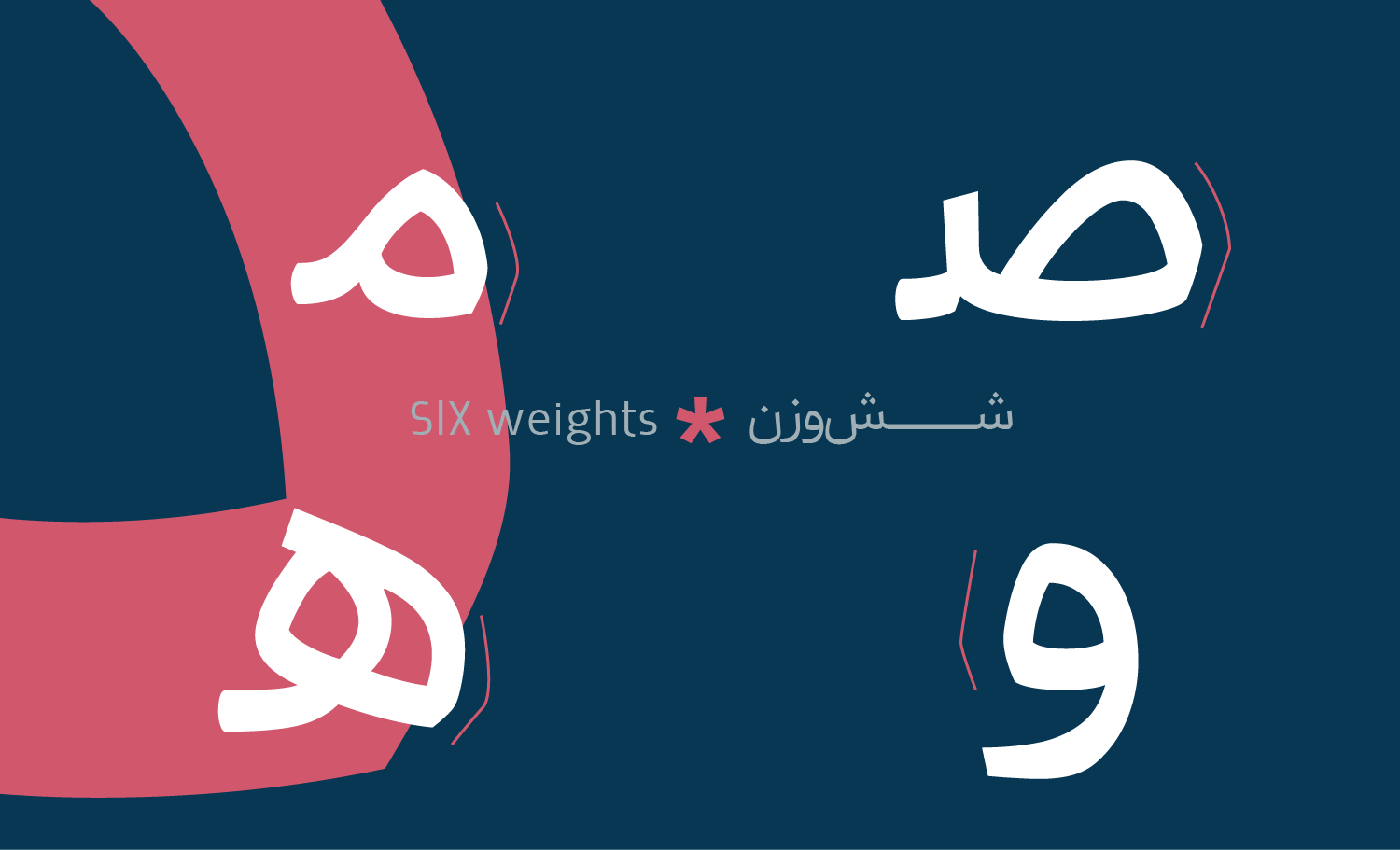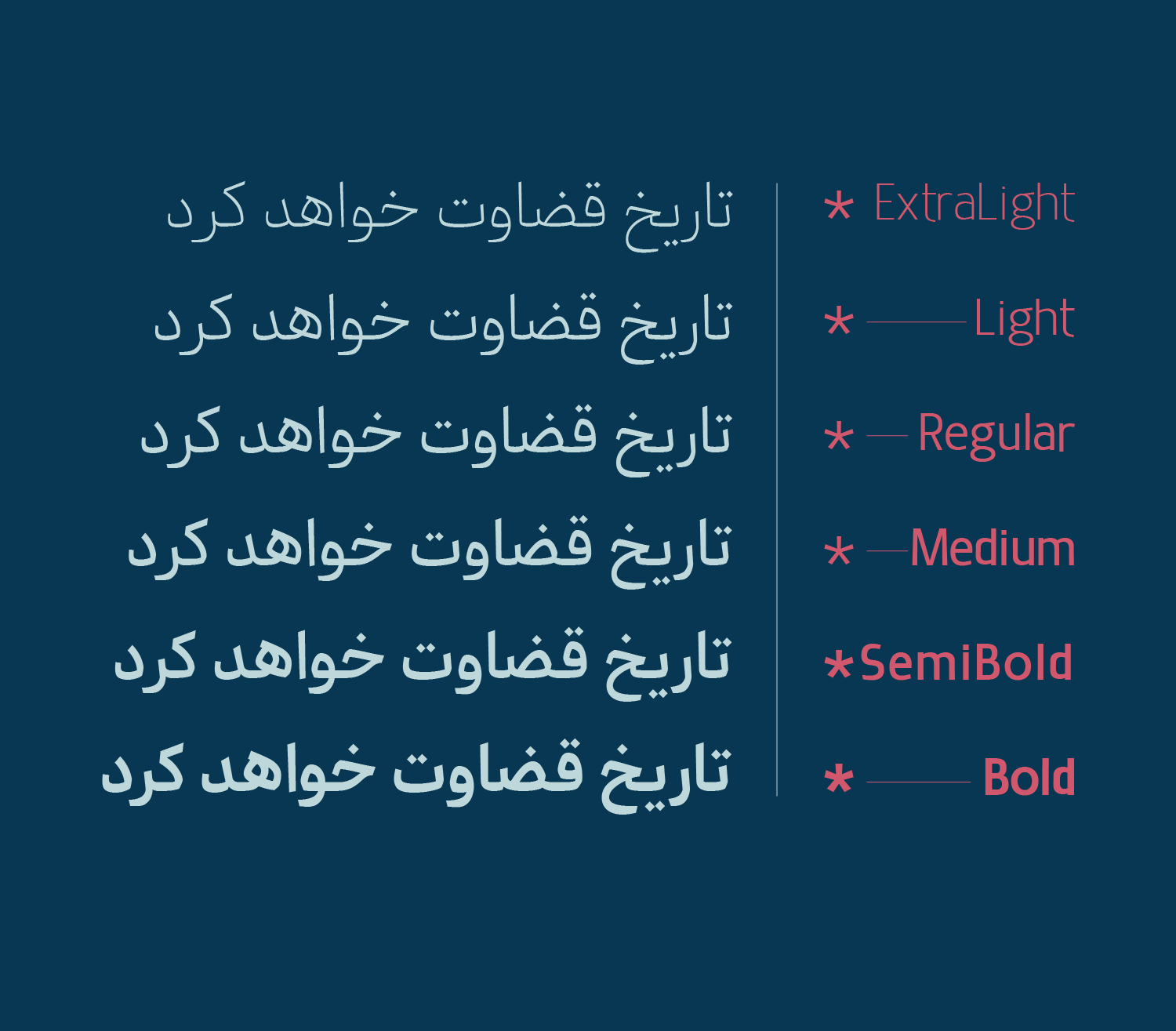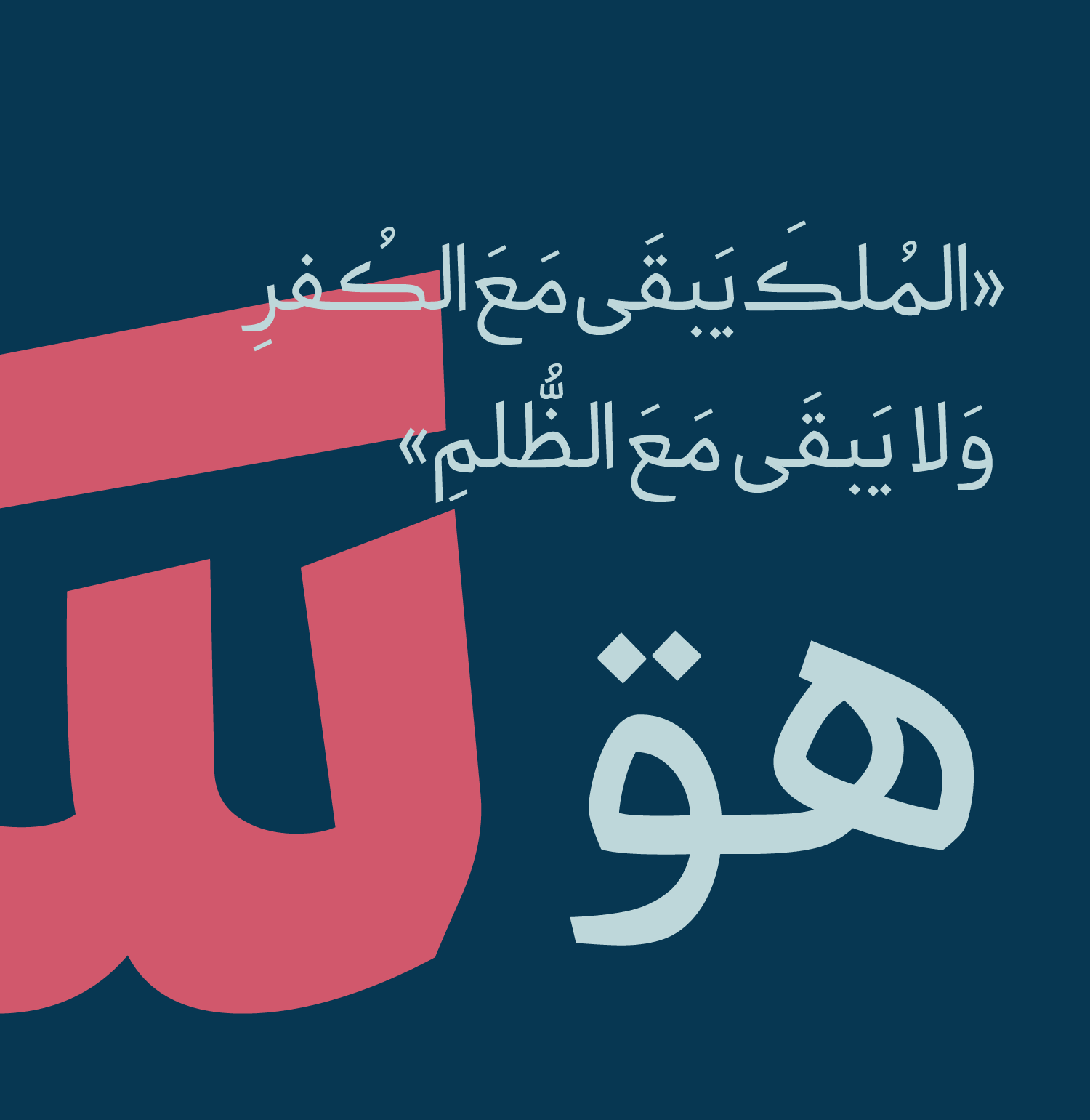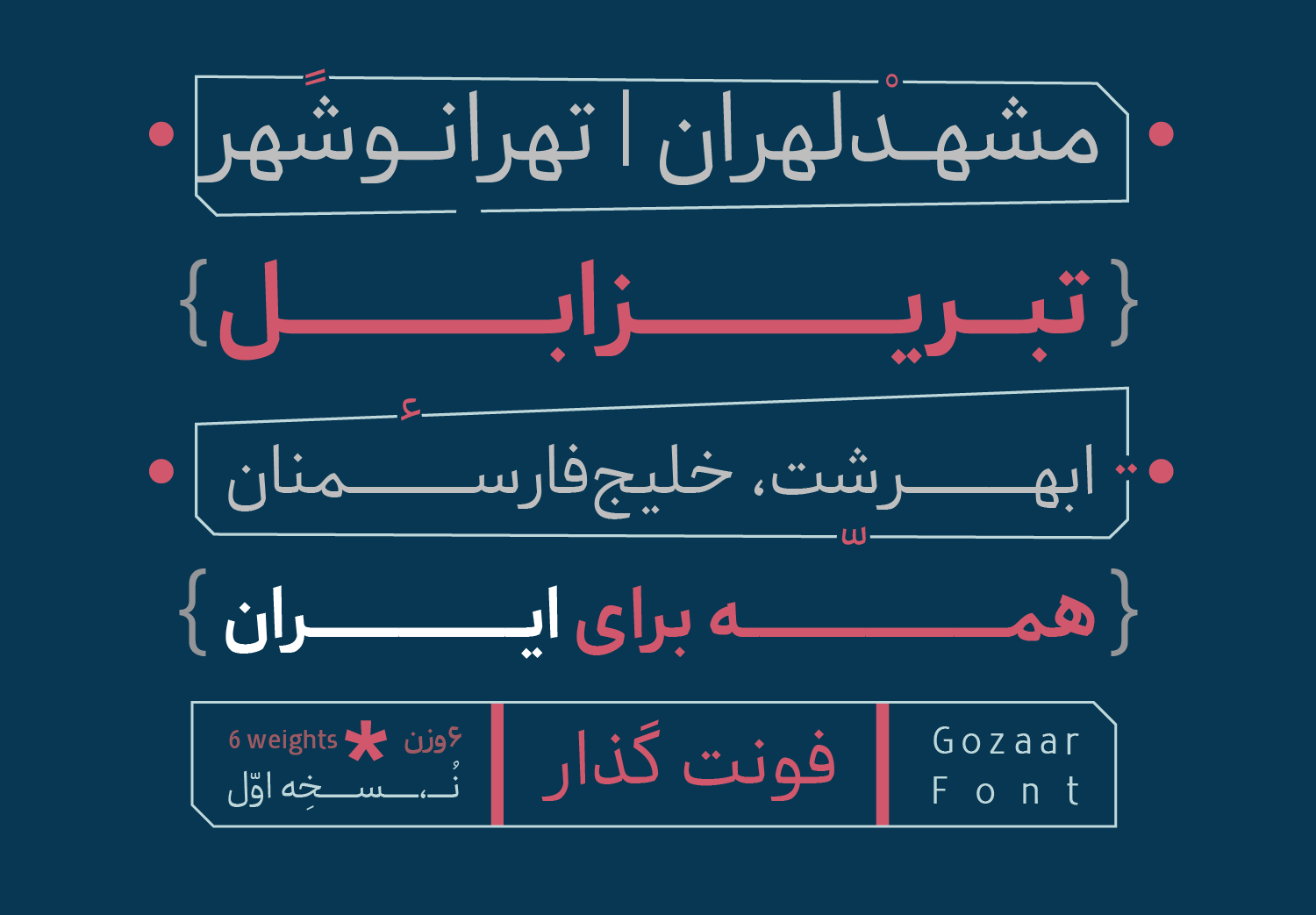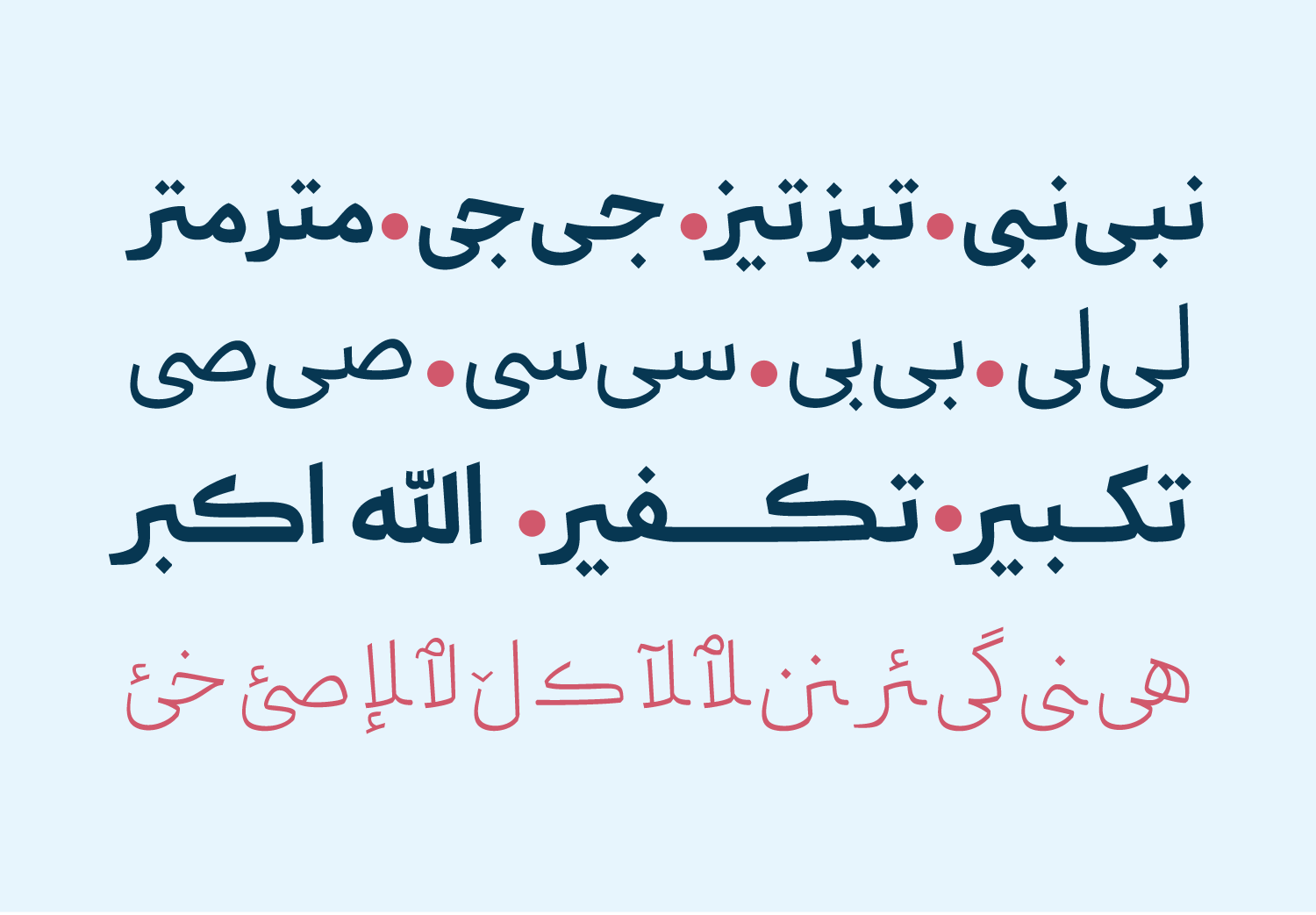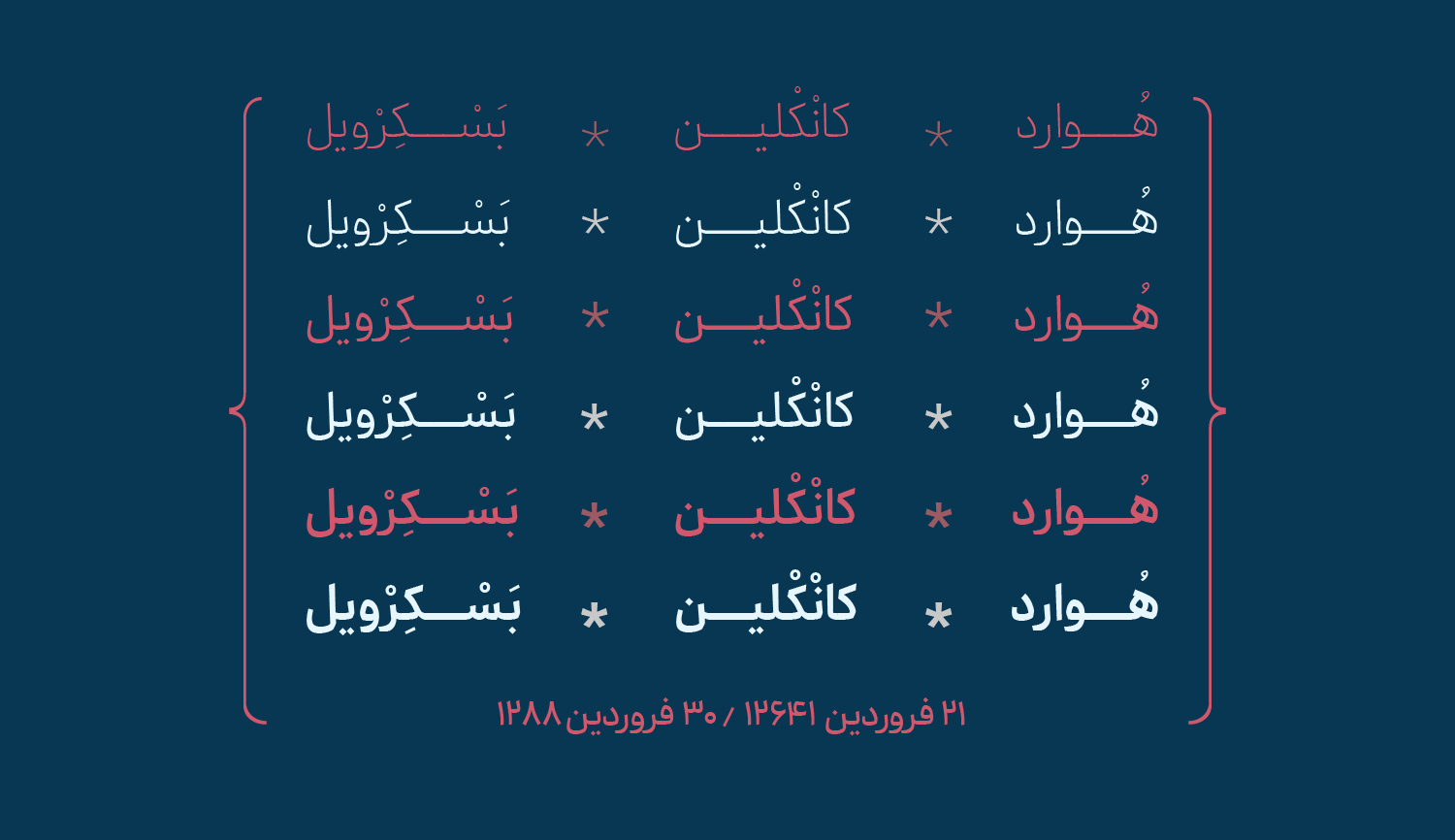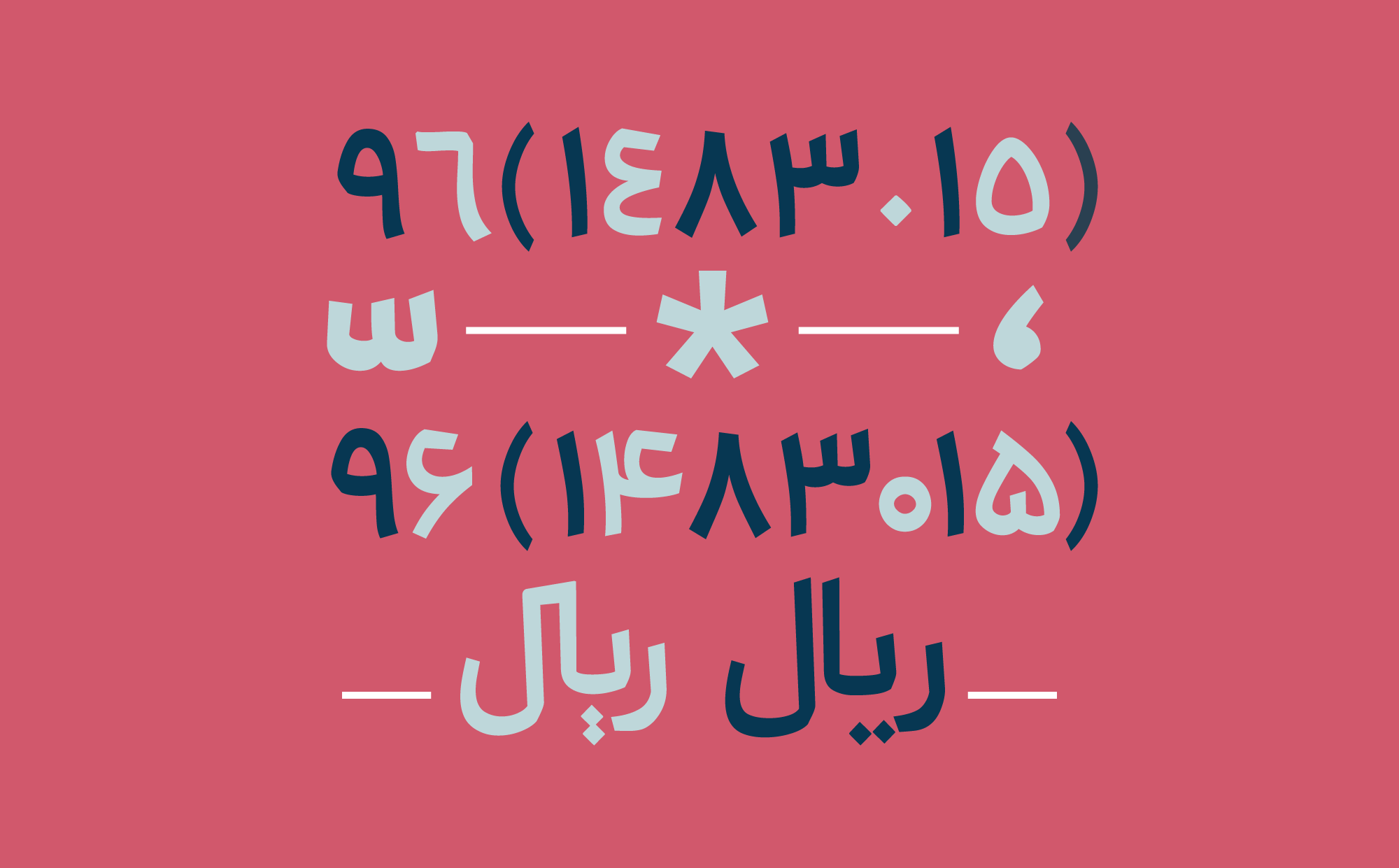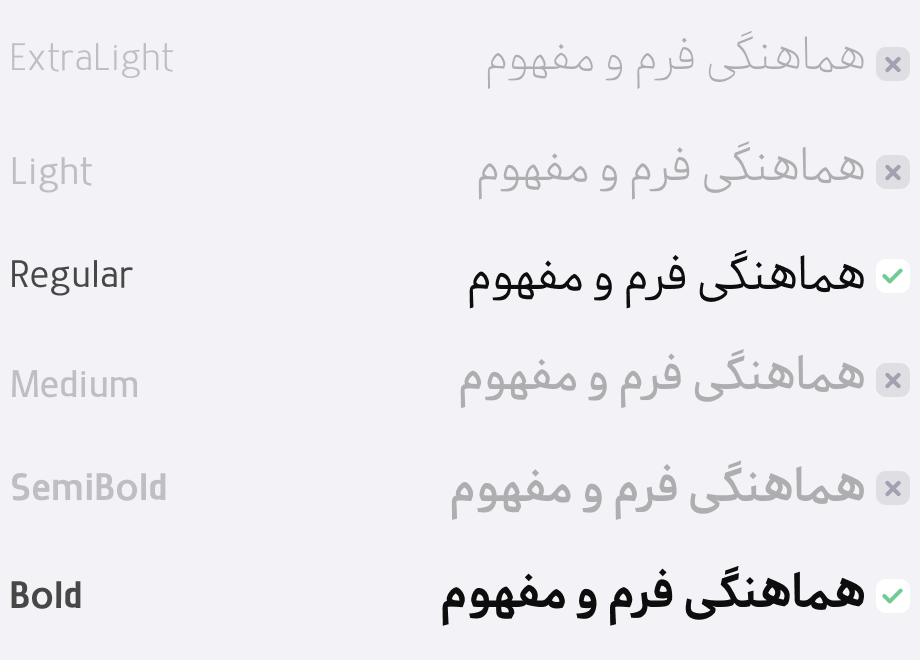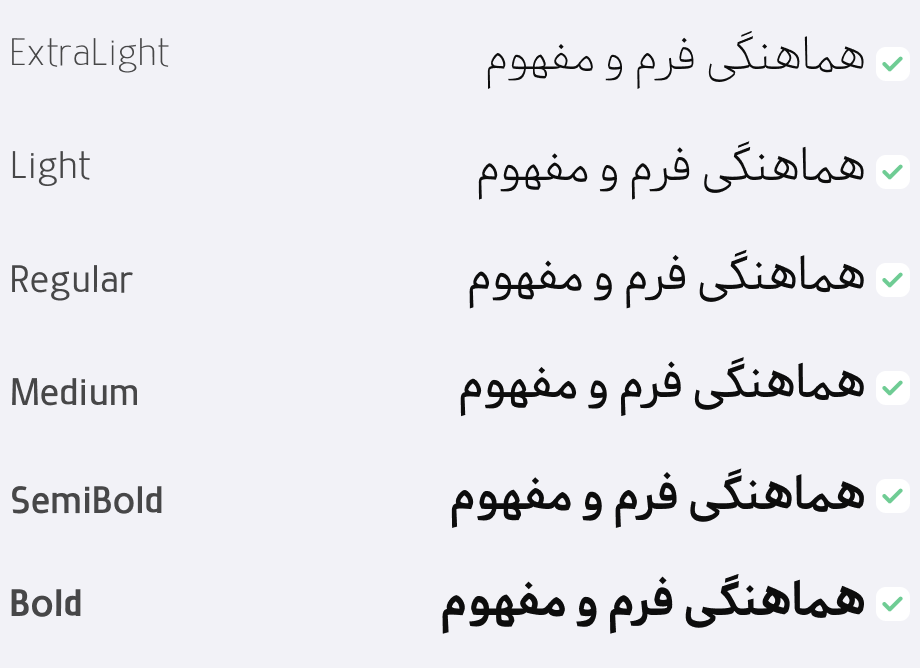
نسخه اولیه این فونت در ۶ وزن :
ExtraLight-Regular-Medium-Bold-Semibold-Bold
در اختیار شما قرار گرفته است .
تمامی حروف و مفردات با حفظ استقلال خود دارای فرم های یکپارچه هستند که رفتارهای نمایشی در وزن های بالا بیشتر به چشم می خورد .
مهرداد نوتاش فارغ التحصیل رشته گرافیک، از سال 1396 فعالیت طراحی تایپ را زیر نظر استاد دامون خانجانزاده آغاز کرده است. او از سال 1385 فعالیت حرفه ای خود را با اشتغال در آژانسهای تبلیغاتی و استدیوهای دیزاین آغاز کرده است. وی در چند جشنواره خارجی وداخلی طراحی پوسترنیز حضور داشته است . او هم اکنون به عنوان مدیر خلاقیت مشغول به کار است .